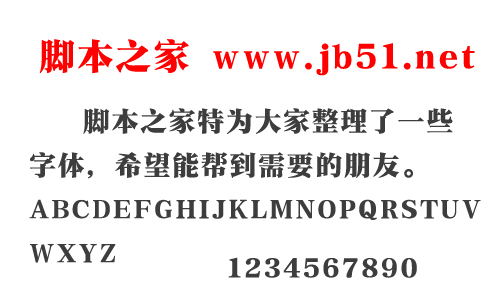
騰祥銘宋簡-W11字體是騰祥公司自主精心設計開發(fā)的正文字體。一共有11款粗細,以銘宋W1至W11命名,以期滿足用戶不同領域的用字需求,可用于大標題、銘宋作為宋體里較為規(guī)整的,標題、正文、海報、大型牌匾及屏幕顯示。整個系列風格完全一致,不管是常用字或是非常用字,字字精美、結構端正、重心平穩(wěn)、美觀實用。其中W11為特粗體一款適用于大標題、標題、小標題、正文、平面設計及屏顯用字、大型戶外廣告等。歡迎喜歡騰祥銘宋簡-W11字體前來下載使用。